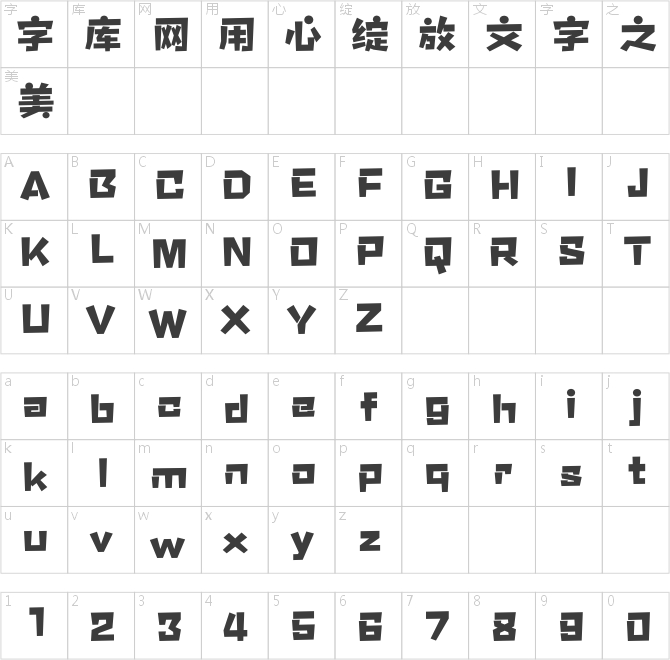
方正雅珠體簡(jiǎn)體 Heavy 詳情頁(yè)
方正雅珠體簡(jiǎn)體 Heavy
方正雅珠體簡(jiǎn)體 Heavy字體字庫(kù)是一款讓人賞心悅目、百看不厭的中文字體,適合各類廣告和產(chǎn)品包裝設(shè)計(jì)應(yīng)用,字體大小1.62MB,格式為ttf字體,上傳用戶是373790005,作者/版權(quán)方為方正字庫(kù)